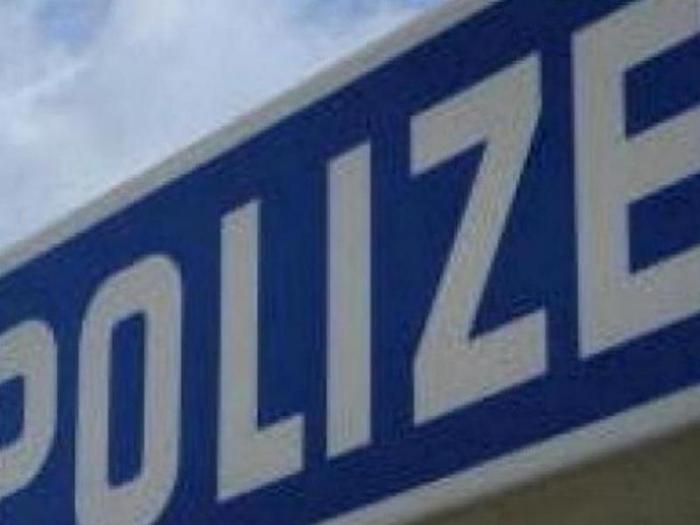
POLIZEI - Schild der Wache u. Bekleidung (etwa um 1980)
Nach einem POLIZEI-Font wird ja immer wieder mal gefragt. Dann geht es aber meist um Fahrzeuge oder andere Länder und Epochen.
Mich würde interessieren, welche Schrift sich hinter den Beispielbildern verbirgt. Ich glaube, es sind die Insignien der 80er. DIN Engschrift müsste man hier stärker als nur in bold condensed haben, um zu diesem Ergebnis zu kommen. DIN condensed black hat hingegen eine völlig andere Anmutung.
Das ist eben keine der feintypografisch überarbeiteten (was auch immer) DIN -Schriften, welche die wesentliche Anmutung der DIN 1451 übernommen haben, aber eben auf Satzschrift mit diversen Schriftgewichten überarbeitet wurden, sondern eben die offizioelle Verkehrszeichen-DIN 1451 Mittelschrift nach dem im jeweiligen Jahr gültigen Normblatt, díe eben zu dieser Zeit noch deutlich diese Hilfsraster mit Strichstärke = 1/7 der Versalhöhe
Nach 1451 auf jeden Fall, aber ich glaube, bei Mittelschrift hast du dich vertan. Ich sehe da die Komponenten der Engschrift und frage mich, warum man die nicht bis extra bold ausgebaut hat.
Die hat man nicht extra Bold ausgebaut, weil dies die Norm nicht vorsah, da war eben Strichstärke = 1/7 Versalhöhe, basta!
Das DIN und gute Gestaltung oft 2 Paar Schuhe sind, wurde hier ja schon oft festgestellt.
Wenn man das "O" auf Kleidung und Revierschild vergleicht unterscheiden sie sich schon mal.